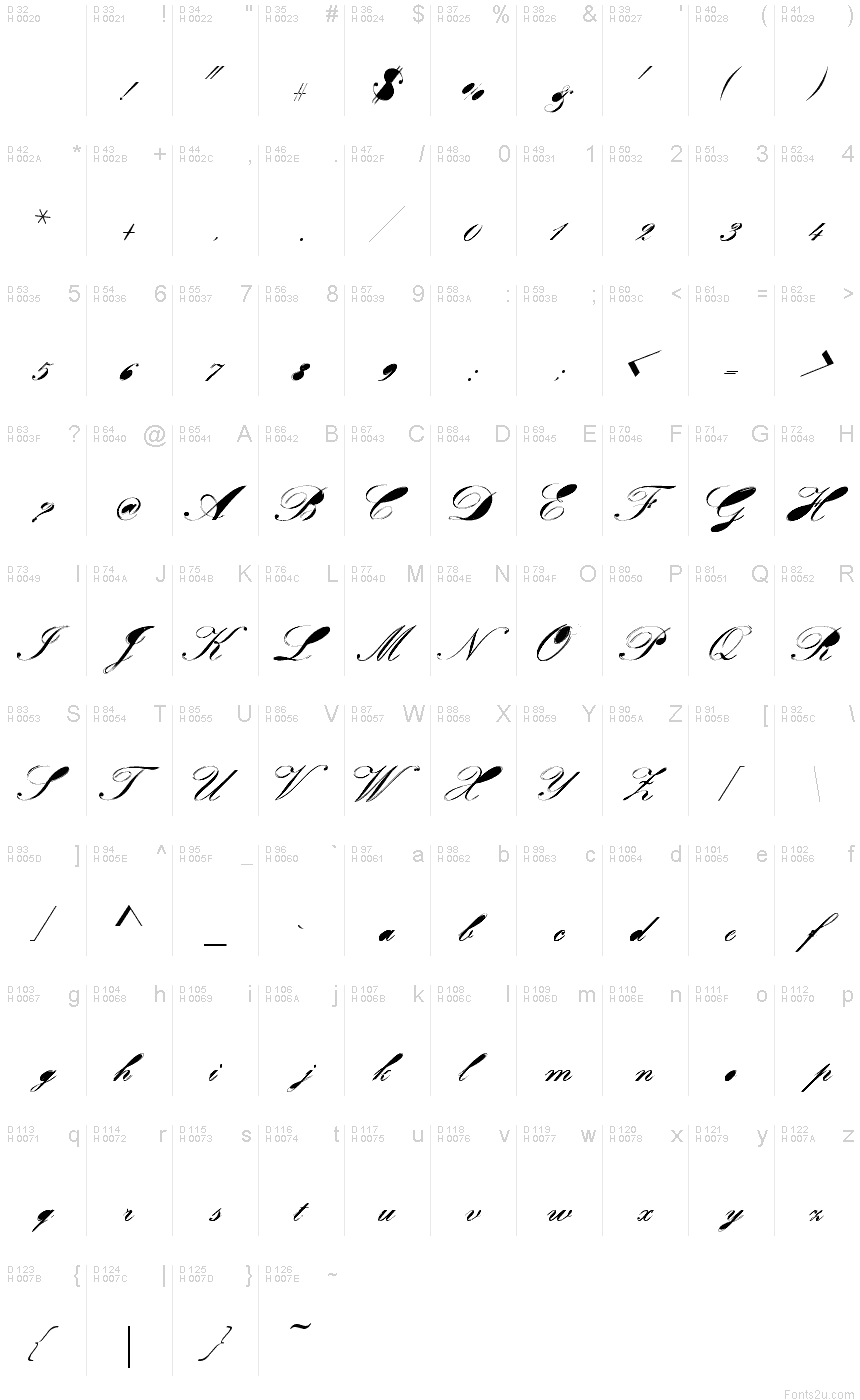
Velvet
Velvet od Faizal Rezy to bezpłatny kaligraficzny krój pisma, utrzymany w błyszczącym klimacie zaproszeń z końca lat 90. Litery suną w przód długimi, jedwabistymi pociągnięciami, łącząc dramatyczny początkowy zawijas z zaokrąglonymi, zapętlonymi małymi literami, dzięki czemu font jest płynny, a nie sztywny.
Naturalnie pasuje do opakowań kosmetyków, logotypów butików, papeterii ślubnej, menu kawiarni czy nagłówków w magazynach, gdzie ten bezpłatny font nadaje miękki, ręcznie pisany charakter. Użyj go, gdy chcesz, aby krótkie tytuły, monogramy czy podpisy wyglądały elegancko i nieco teatralnie – wydłużone zawijasy same zadbają o styl.